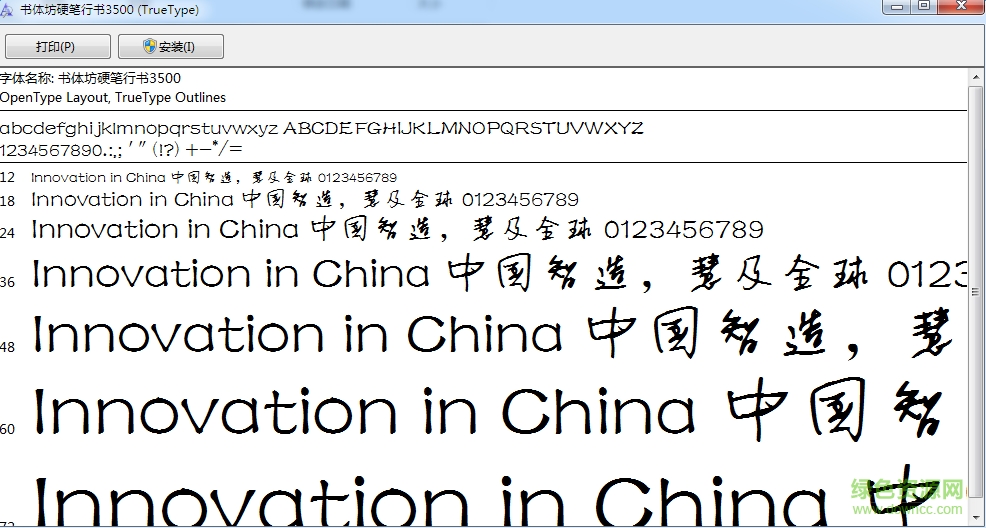
書體坊硬筆行書3500
書體坊硬筆行書3500是一款收錄有3500常用漢字的電腦硬筆行書字體,為了書寫簡便,行書書法對楷書的某些部位作了簡化,或減省點畫,或并合線條,有一種獨特的魅力,喜歡的朋友可以來綠色資源網(wǎng)下載!
書體坊硬筆行書3500由書體坊版主禚效鋒書寫,共收錄中文常用字3500字,字體看上去流暢、清秀、工整、剛勁、緩如情絲、急如神兵、蒼勁,力透紙背,流利,抑揚頓挫,秀麗!